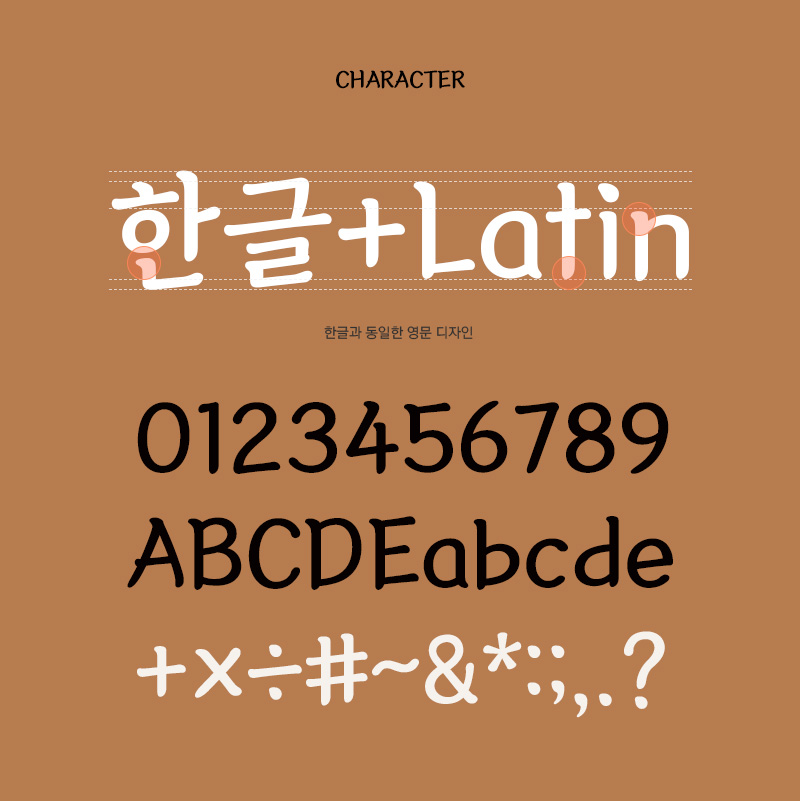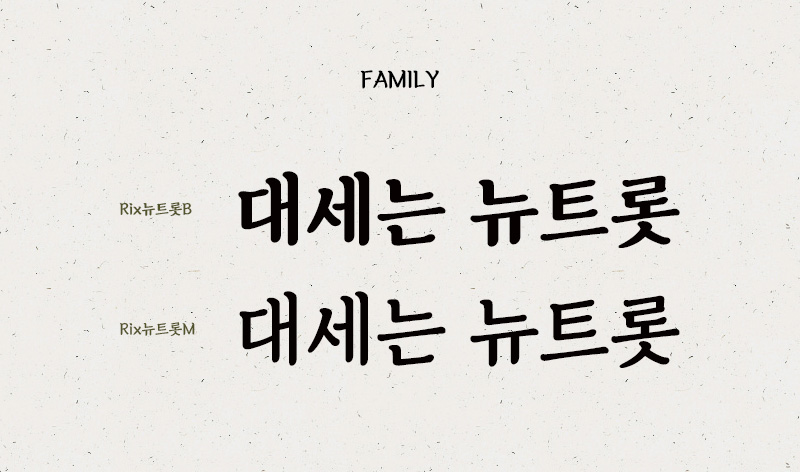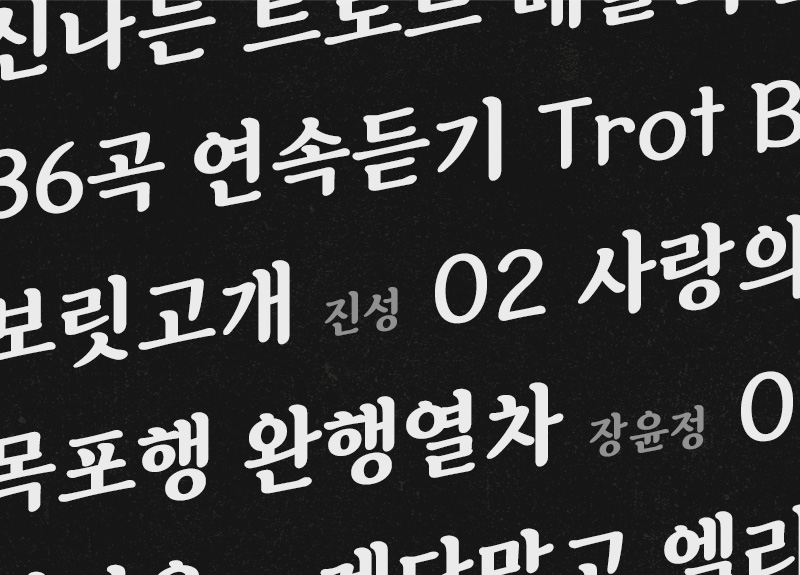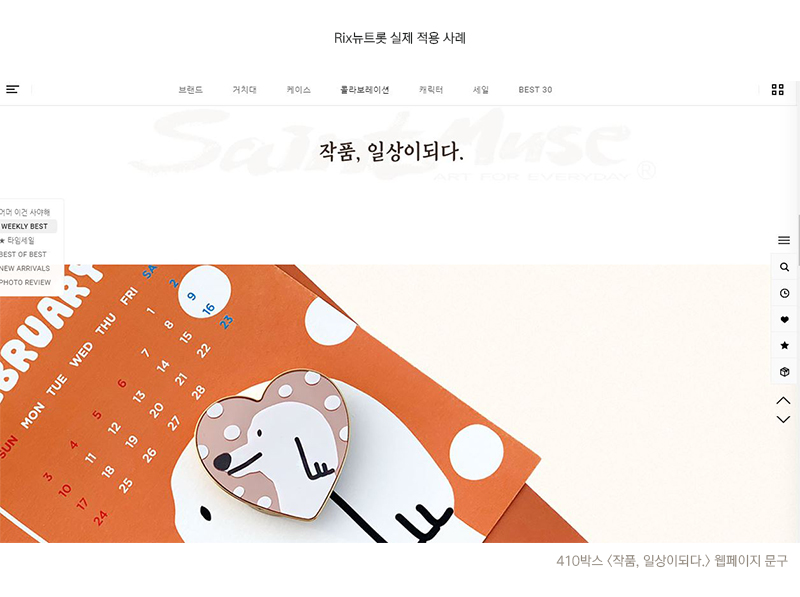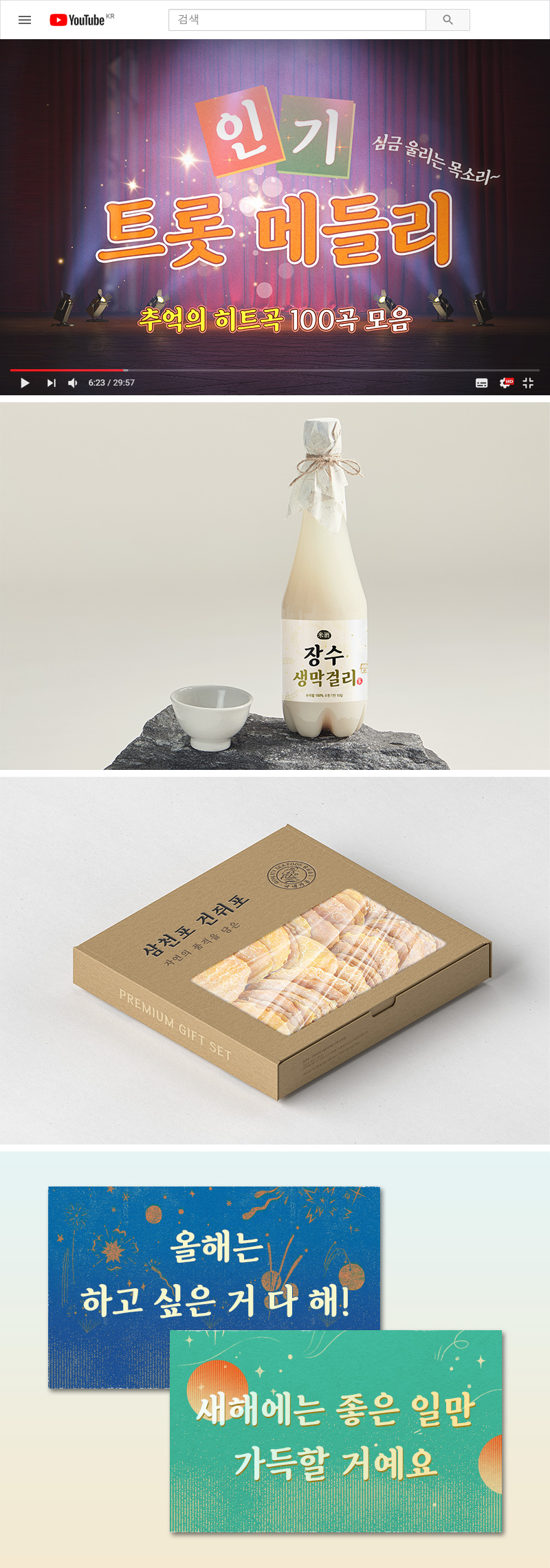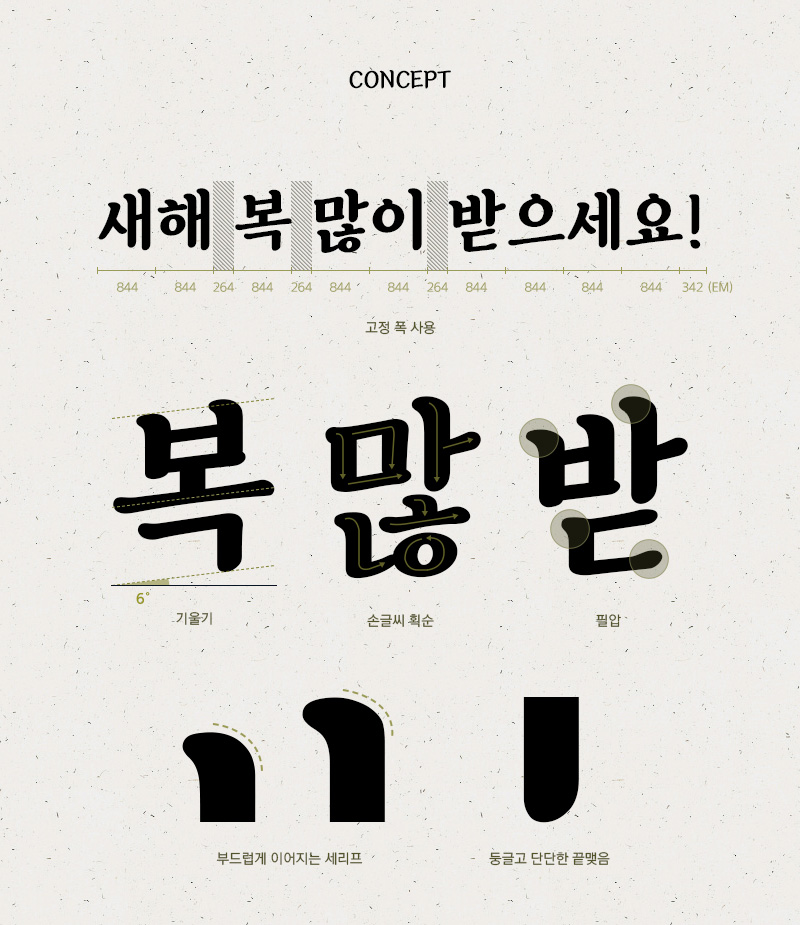
RixNewtrot
2 Style - Bold, Medium
Rix뉴트롯은 뉴트로 감성과 경쾌한 트로트를 모티브로 제작한 명조형 손글씨 서체입니다.
획대비와 강약 조절, 적절한 기울기로 리듬감을 주며 두 가지 굵기로 활용도를 높였습니다.
FontFamily Rix뉴트롯 / RixNewtrot
Design Park Yun-sang
Direction Park Yong-rak
손글씨 획순을 따르고 강약 조절을 주어 필압이 느껴지며, 기울기를 통해 손으로 쓴 듯한 느낌을 주었습니다.
자소 간의 크기감을 통하여 세리프의 크기를 조절하여 비율을 맞추었습니다.
한글에서 나타나는 특징들을 영문 디자인에 동일하게 적용하였습니다.
두 가지 굵기로 제작하여 사용성의 폭을 넓혔습니다.